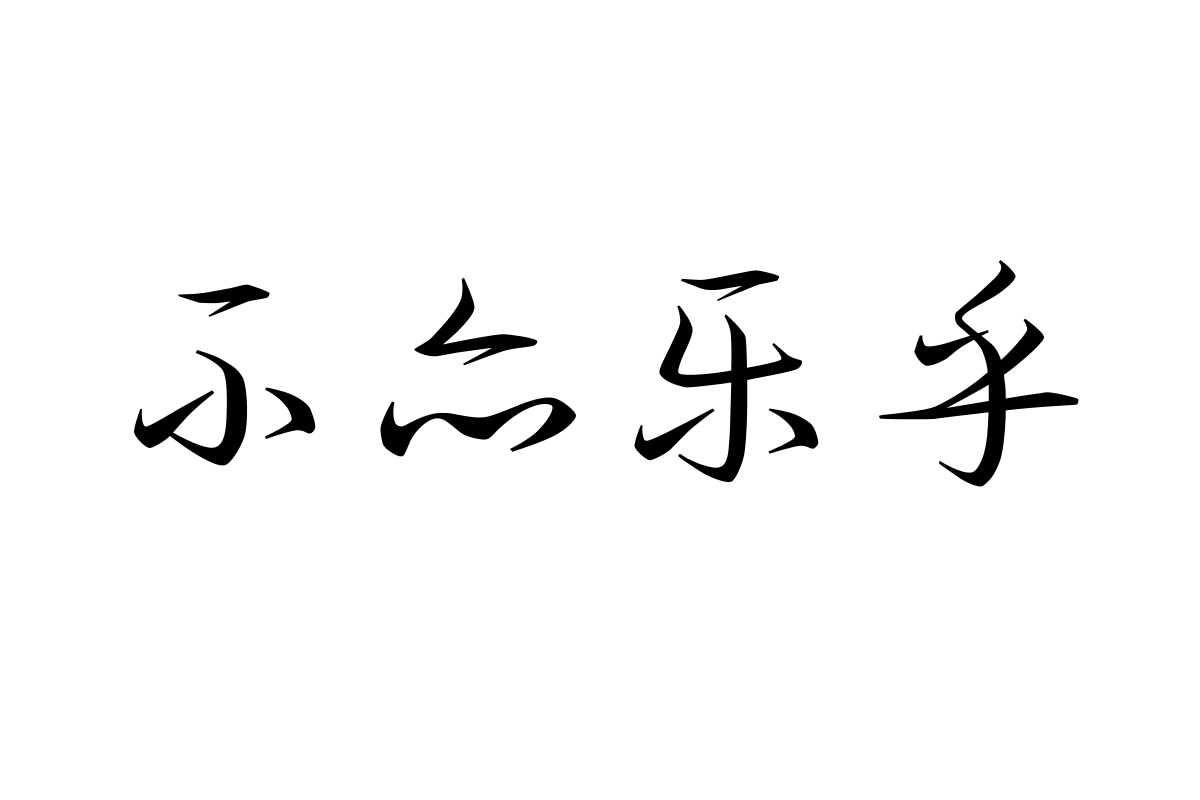
汉仪妙草是一款现代感十足的中文字体,由汉仪字库出品。这款字体以其简洁、流畅的线条和优雅的字形结构,为文字赋予了一种独特的艺术美感。
汉仪妙草采用了现代设计手法,将传统的汉字书写风格与现代审美相结合,使得字体既保留了传统文化的韵味,又具有鲜明的时代特色。它的笔画粗细适中,线条流畅自然,无论是用于标题、正文还是装饰性文字,都能展现出其独特的魅力。
汉仪妙草的字形结构紧凑而不失灵动,给人一种轻松愉悦的感觉。它适用于各种场合的文字设计,包括广告、杂志、报纸、网站等,能够很好地传达出设计师想要表达的主题和情感。